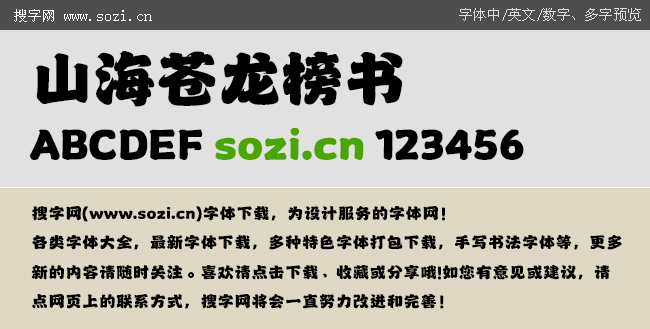
山海蒼龍榜書
搜字網(wǎng)提供一款山海蒼龍榜書中文字體下載,山海蒼龍榜書是一款手寫風(fēng)格的毛筆字體。榜書古時(shí)又稱作署書,是書寫在匾額上的大字,山海蒼龍榜書字體粗壯有力,字形端莊大氣,視覺效果非常不錯(cuò)。適合標(biāo)題設(shè)計(jì)、海報(bào)設(shè)計(jì)、廣告設(shè)計(jì)等應(yīng)用。